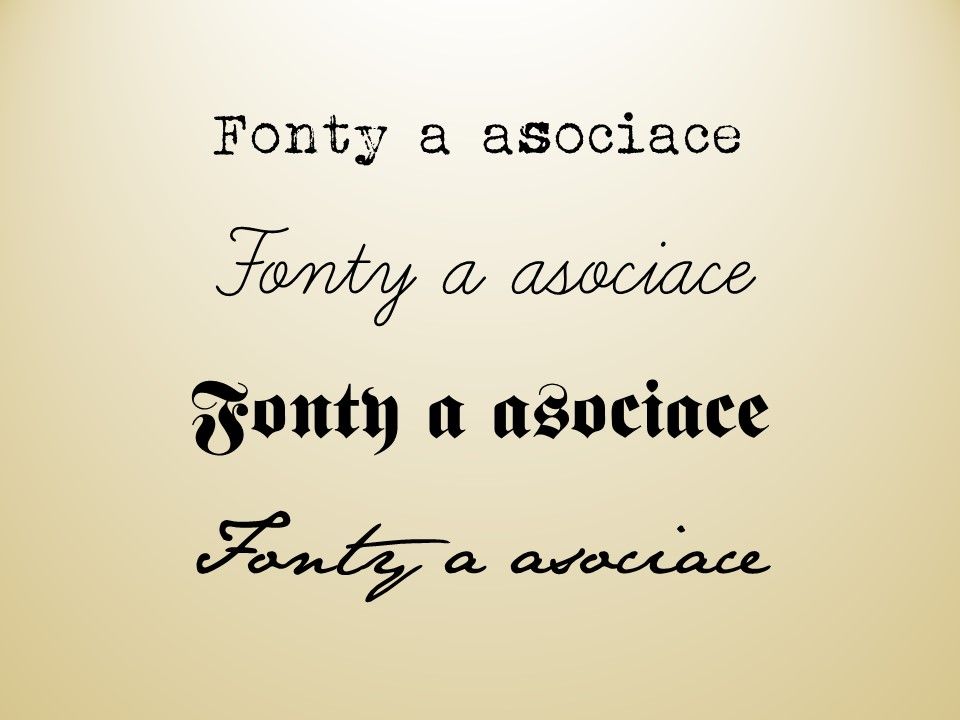
PSYCHOLOGIE FONTŮ
Vdechněte svým textům duši
JAK VYBÍRAT FONTY
Je jedno kam font vybíráte. Je jedno, pro koho font vybíráte. Ale jsou věci, které musíte vědět, abyste vybrali font, který funguje.
FONTY, EMOCE A ASOCIACE
Vnímání fontů člověkem má svá pravidla a jejich výběrem předáváte jasné a konkrétní informace podvědomí čtenáře. Fonty na nás působí jak svým vzhledem, tak díky asociacím, které v nás probouzí.
FONTY A JEJICH VZHLED
V každém textu vnímáme tvary písmen, mezery mezi nimi i vzájemné proporce čar a křivek. To vše na nás působí a vyvolává ve vašem podvědomí reakci. Sklon písma, řád, křivky, to všechno je součástí vzhledu fontu a okamžitě ovlivňuje naše vnímání. A vzbudí emoce.
FONTY A NAŠE ASOCIACE
Co vás napadne jako první, při pohledu na tyto fonty? Psací stroj, školní docházka, osobní dopis nebo 2. světová válka? To jsou asociace, které má většina z nás. A které můžeme využít při výběru fontů. Asociace kulturní, historické, společenské nebo asociace spojené se silnou značkou.
PROČ PSYCHOLOGIE FONTŮ?
„U každého slova, které čteme, vnímáme nejenom jeho obsah, ale i formu. Proto jsou fonty velice důležitou součástí celkového designu i značky. Velmi často podceňovanou.“
Fonty jsou velice důležitou součástí celkového designu, stejně jako například barvy. Forma by vždy měla ladit s obsahem.
Font sám o sobě má obrovskou moc ovlivnit vnímání čtenářů a tím i to, jestli vám budou věřit nebo ne.
Font je nedílnou součástí vizuální identity firmy či podnikatele a stojí za to si ho vybrat s jasným záměrem.
Výběr fontu podle OSOBNOSTI
Fonty dokonale odráží to, jací doopravdy jste. Popíšou váš charakter, hodnoty i nastavení vůči druhým.
„Jako webdesignerka se setkávám s výběrem fontů velmi často. Vždy jsem k nim přistupovala obezřetně a s respektem, ale spíše tak, abych nevhodným fontem "nepokazila" celkový design webu. V grafice mám ráda čistotu a minimalismus, takže jsem v 90% případů skončila u jednoduchých bezpatkových fontů. Ty totiž nikoho neurazí, ale ani nenadchnou... Až díky Andree jsem objevila, jak velký rozdíl může udělat font "na míru" s designem a celkovou náladou webu.“
„Font, použitý na webu nebo na vizitce, vyjadřuje osobitost, ovlivňuje vnímání a dokresluje celkový dojem. Má moc přitáhnout ty správné klienty a odradit ty ostatní. Dovoluje vyjádřit atributy, jako je důvěra, jednoduchost, péče, něžnost nebo síla. Proto dává smysl věnovat volbě fontu stejnou pozornost jako výběru barev, ilustračních fotografií nebo sloganu. A proto považuji psychologii fontů za velmi užitečný marketingový nástroj.“